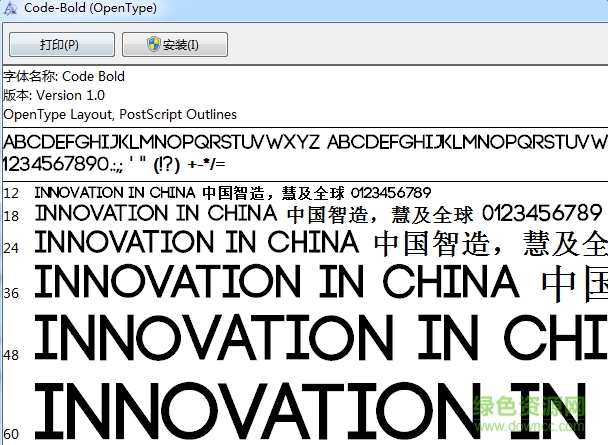
Sherlocode字體是一款超好用的英文個(gè)性字體,該字體具有自己獨(dú)特的風(fēng)格,深受廣大平面設(shè)計(jì)師的喜愛(ài),適用于廣告設(shè)計(jì)等領(lǐng)域,需要的用戶就趕快來(lái)綠色資源網(wǎng)免費(fèi)下載收藏吧!
Sherlocode字體是一款極具個(gè)性的字體,該字體十分飄逸,彰顯了自己的個(gè)性,有喜歡的朋友可以來(lái)綠色資源網(wǎng)下載使用!